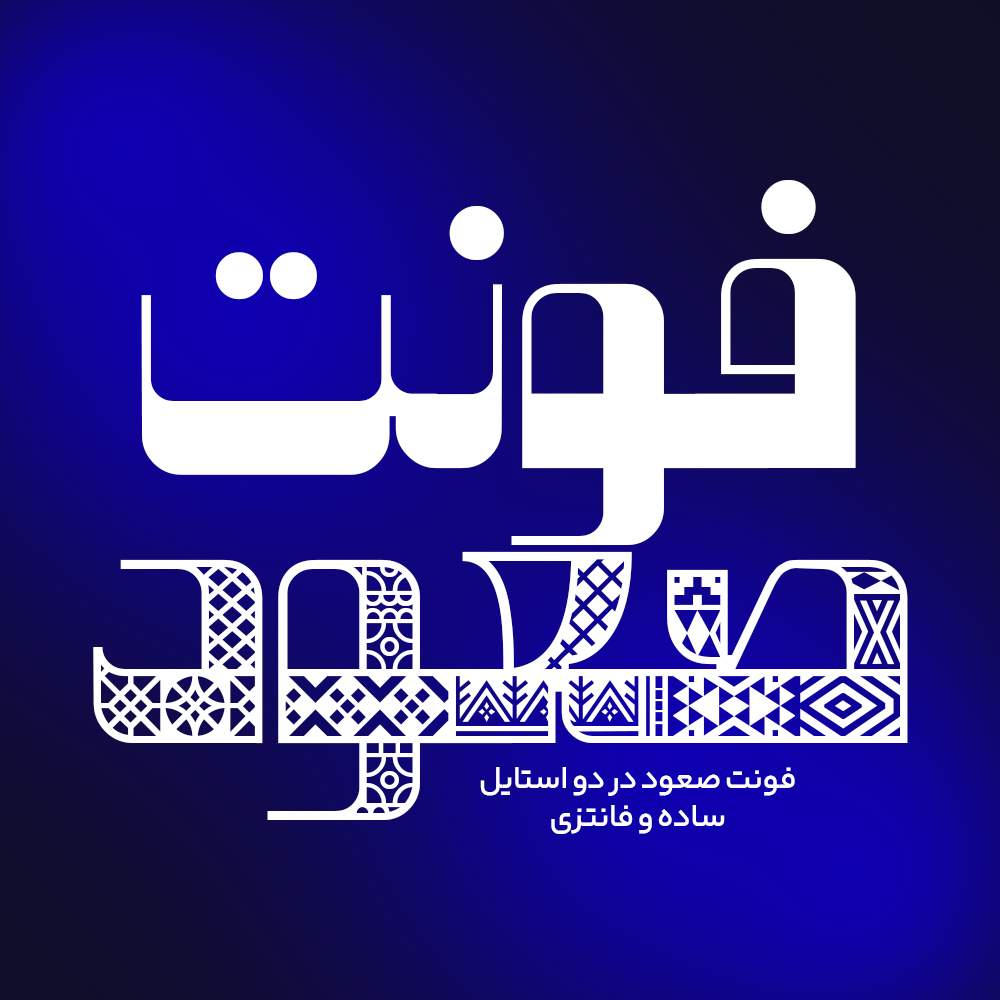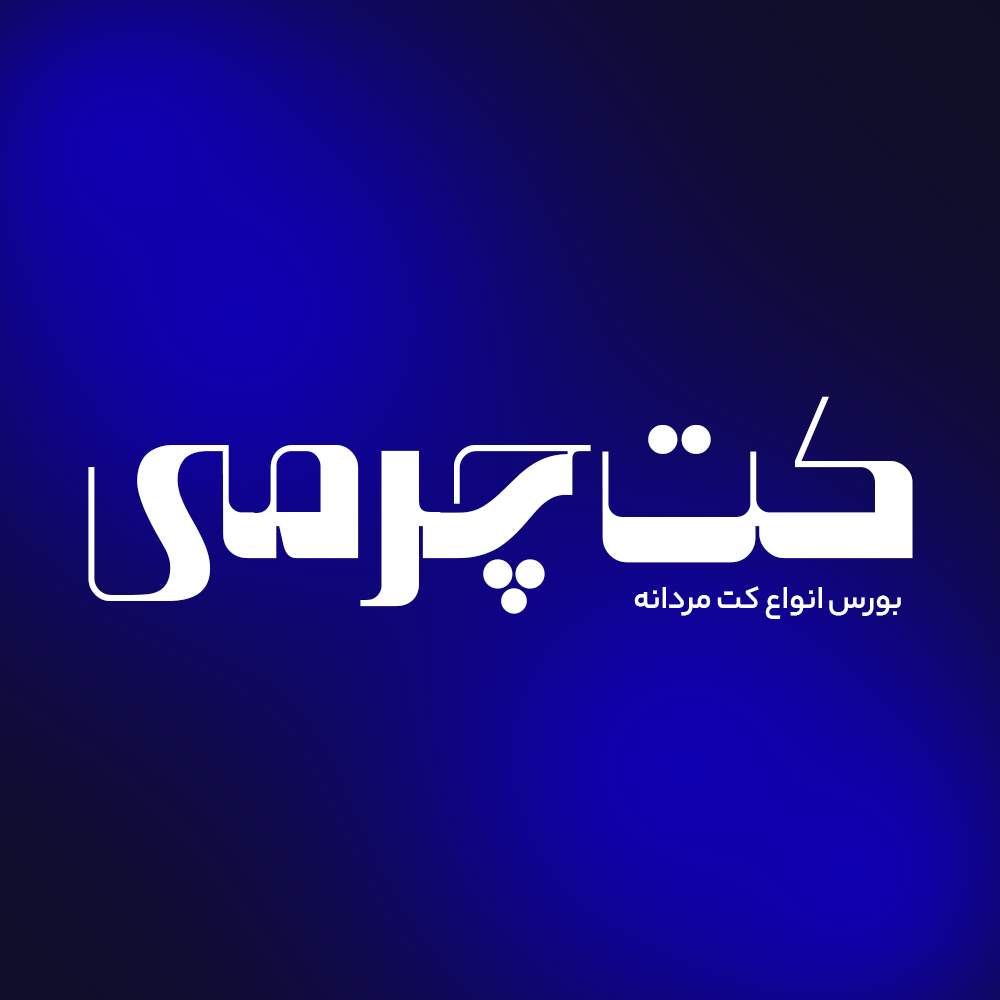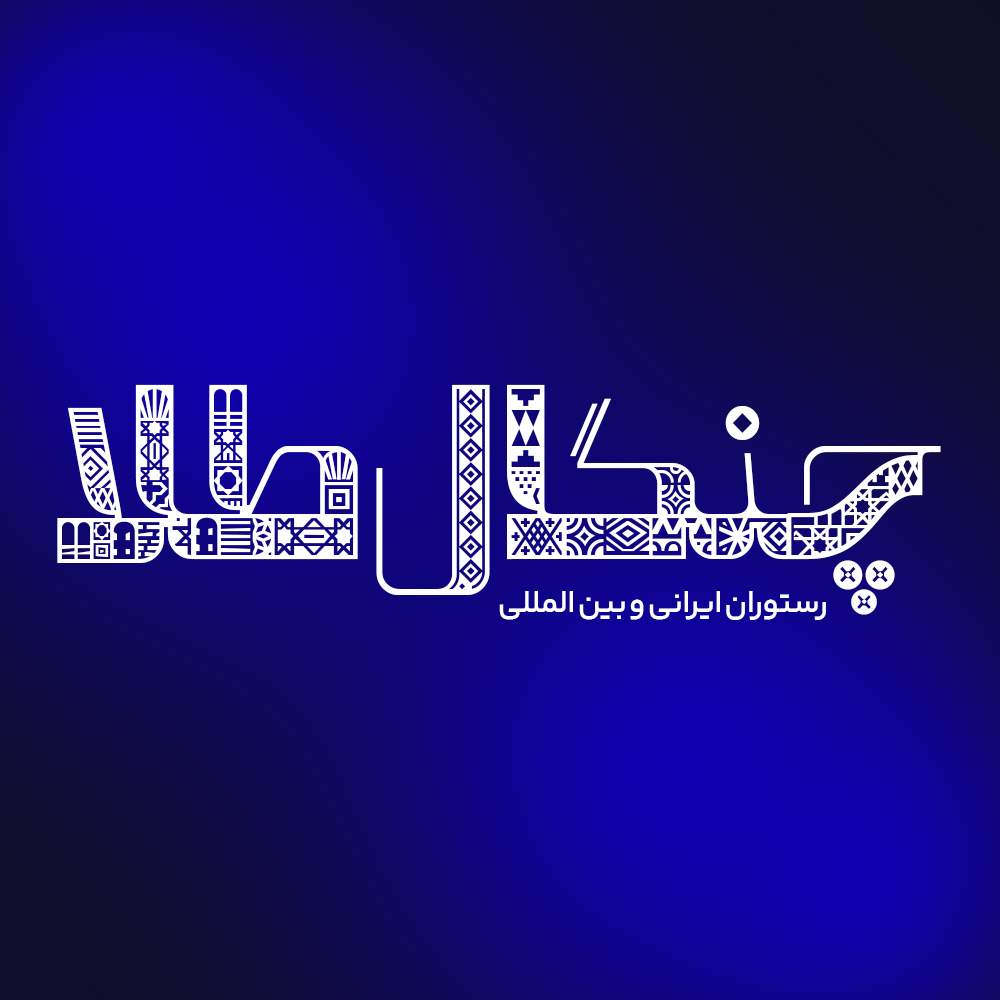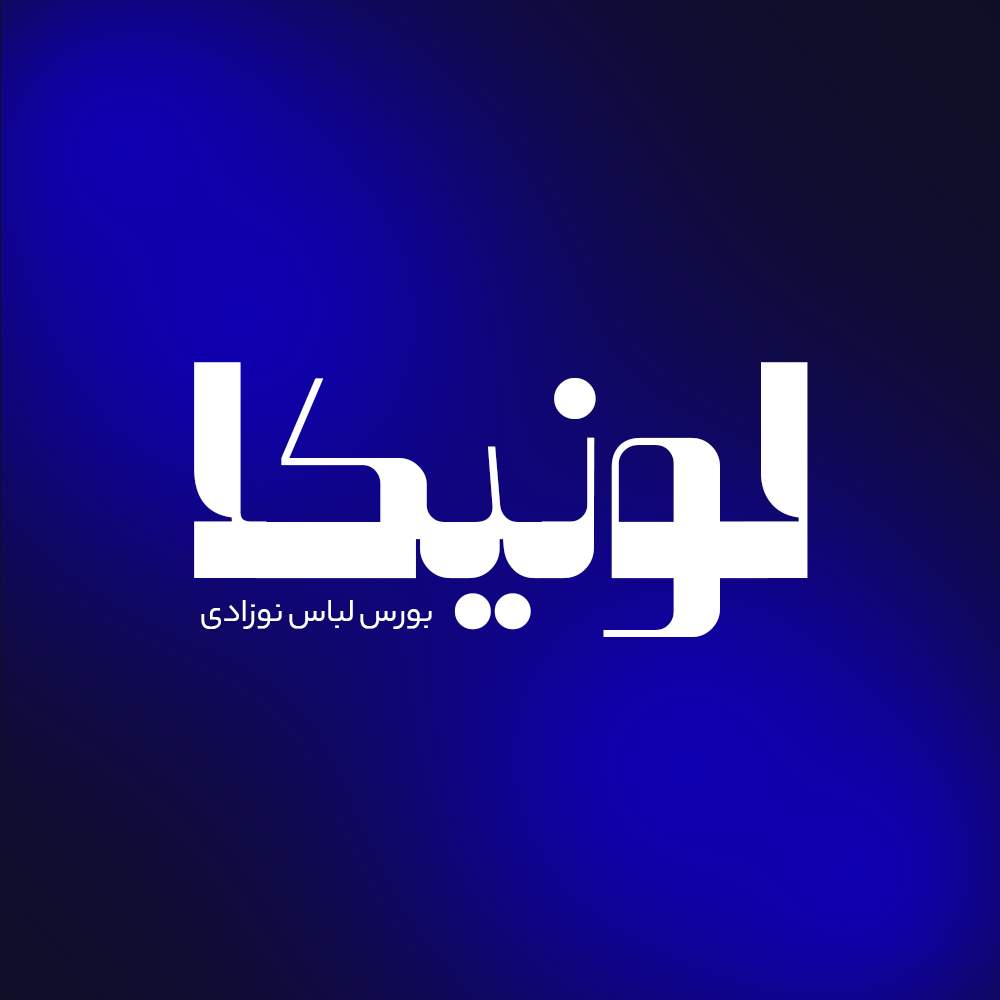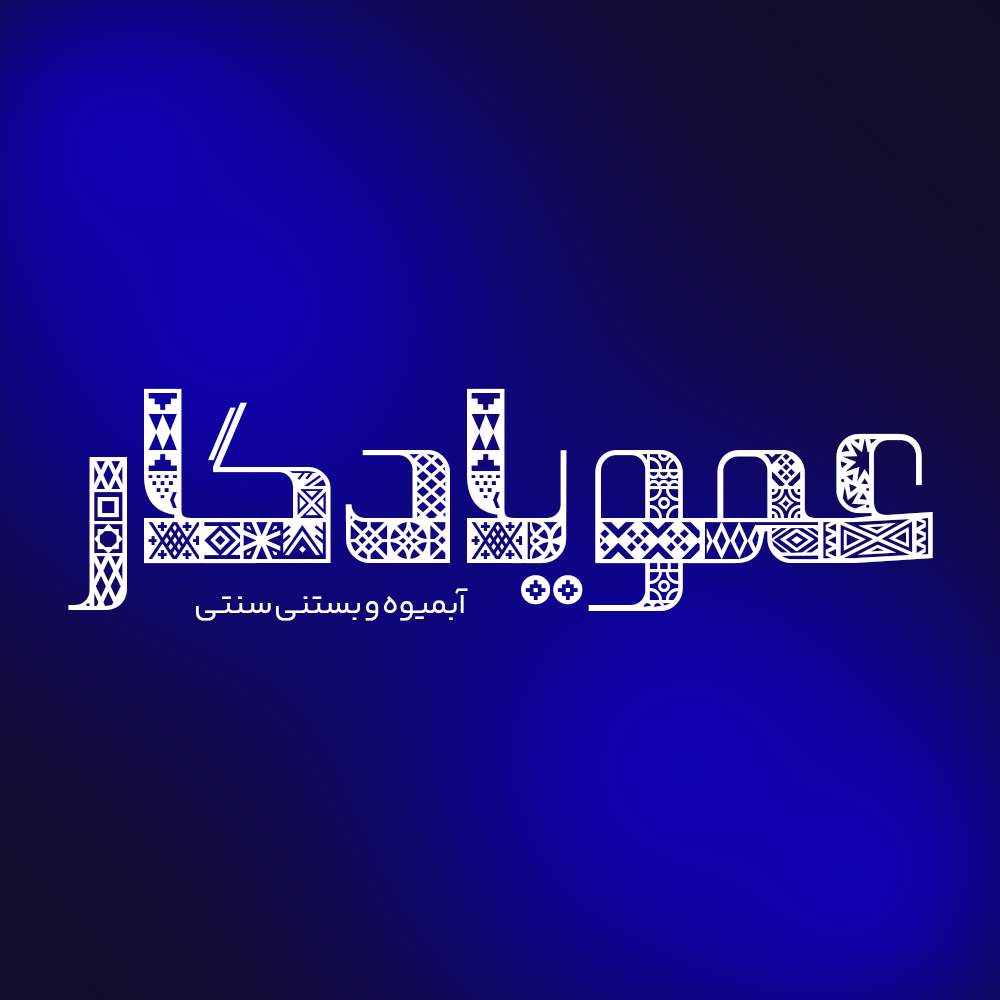
فونت فارسی صعود Soud Font
فونت لوگوتایپ صعود + نسخه جدید فونت فارسی صعود یک فونت فانتزی در دو استایل ساده و فانتزی با کاربرد طراحی لوگوتایپ و طراحی های مختلف…
فونت لوگوتایپ صعود + نسخه جدید
فونت فارسی صعود یک فونت فانتزی در دو استایل ساده و فانتزی با کاربرد طراحی لوگوتایپ و طراحی های مختلف همچون کتاب کودکانه و تولید محتوای متن های کوتاه و عناوین می باشد. این فونت با ساختار حروف منحصر به فرد خود مناسب استفاده در لوگوهای نوشتاری می باشد. همچنین از این فونت در طراحی تابلوهای چلنیوم هم به دلیل ساختار منحصر به فردش می توانید استفاده کنید. در ادامه برای شما نمونه تایپ های این محصول حرفه ای رو آماده کرده ایم که میتوانید مشاهده کنید.
در فرایند بازطراحی فونت صعود چه کارهایی انجام شد؟
- اضافه شدن استایل ساده به فونت
- رفع باگ های گزارش شده توسط کاربران
- بازبینی و تنظیم فاصله گذاری بین حروف
کاربرد فونت فارسی صعود
پیشنمایش و نمونه تایپ های فونت صعود